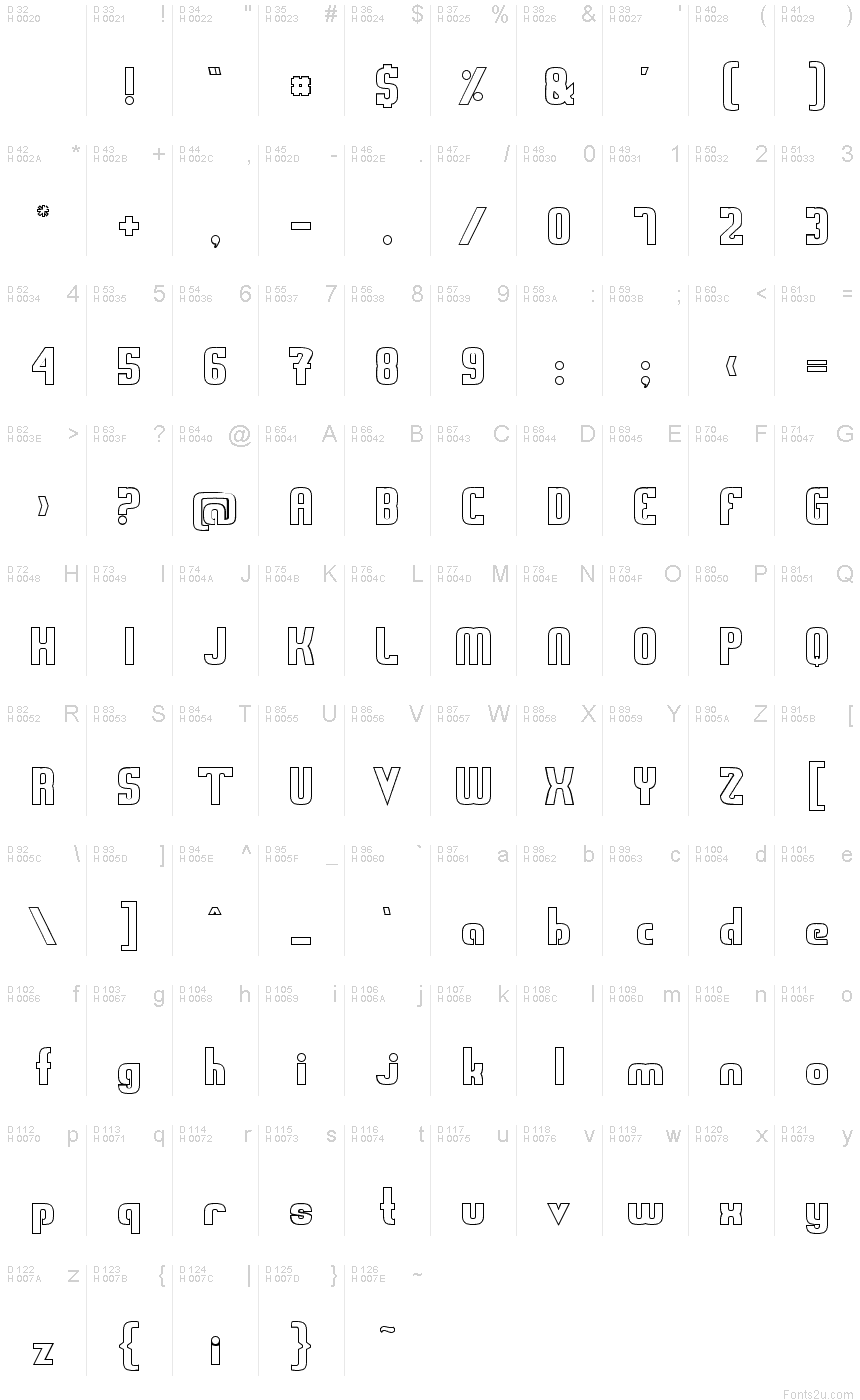
Sweden Funkis StraightOutlined
Sweden Funkis Straight Outlined autorstwa Samuela Parka to nowoczesny, konturowy krój displayowy z nutą zabawnego, nordyckiego retro. Litery zbudowane są z krępych, zaokrąglonych form i równych konturów, co nadaje pismu miękki, plakatowy rytm – jednocześnie geometryczny i lekko groovowy.
Naturalnie pasuje do opakowań, ulotek muzycznych, brandingu kawiarni, plansz tytułowych, nagłówków na okładkach i krótkich projektów logo, gdzie otwarta linia buduje klimat bez zbędnego przekombinowania. Jako darmowy font świetnie sprawdza się w szybkich nagłówkach i monogramach, ponieważ szerokie łuki oraz wysokie, proste kształty zachowują wyrazisty wygląd, nawet gdy liternictwo pozostaje lekkie i przewiewne.